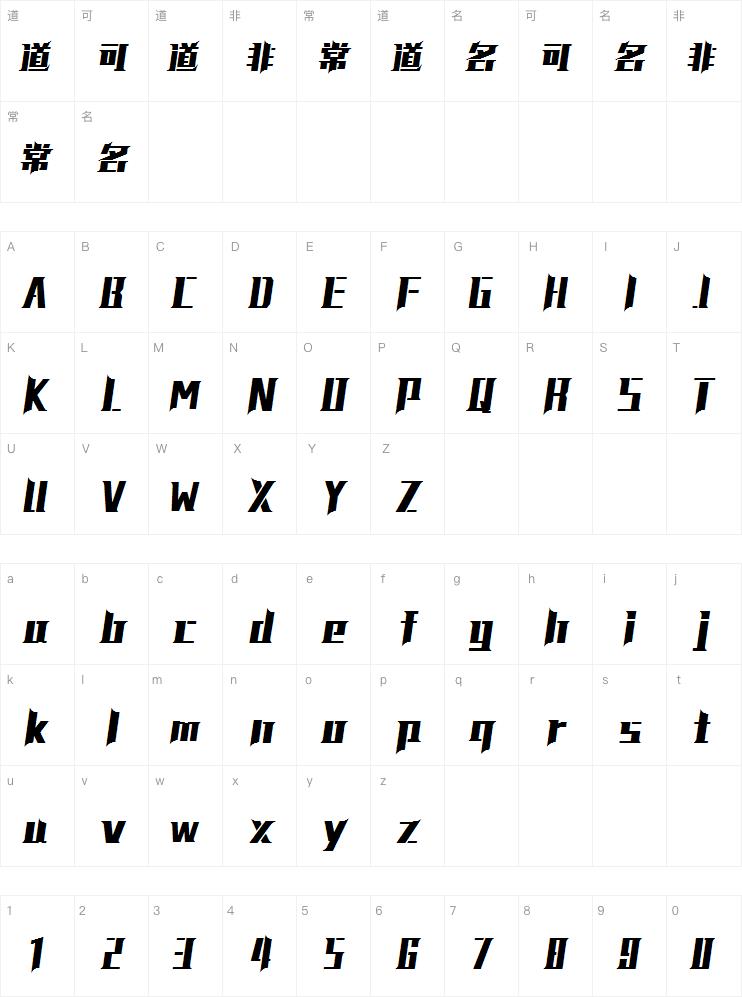
潮笑社讽刺简-闪 特粗
潮笑社讽刺简 特粗是一款具有个性与张力的创意黑体,整体向右侧倾斜,不拘一格,字体粗细是具有横细竖粗的高对比度处理与大标题级别的高灰度设计特点,笔画设计充满张力与装饰性,竖笔画起收笔处、折笔与撇笔有类哥特体或衬线的尖弧装饰角,捺笔画、竖弯钩收笔处带尖角小尾巴特点,应用时这些醒目而尖锐的特点不断出现,刺激着读者的视线往文字上集中。适用于游戏宣传,社交媒体,数码家电等场景。
潮笑社讽刺简-闪 特粗